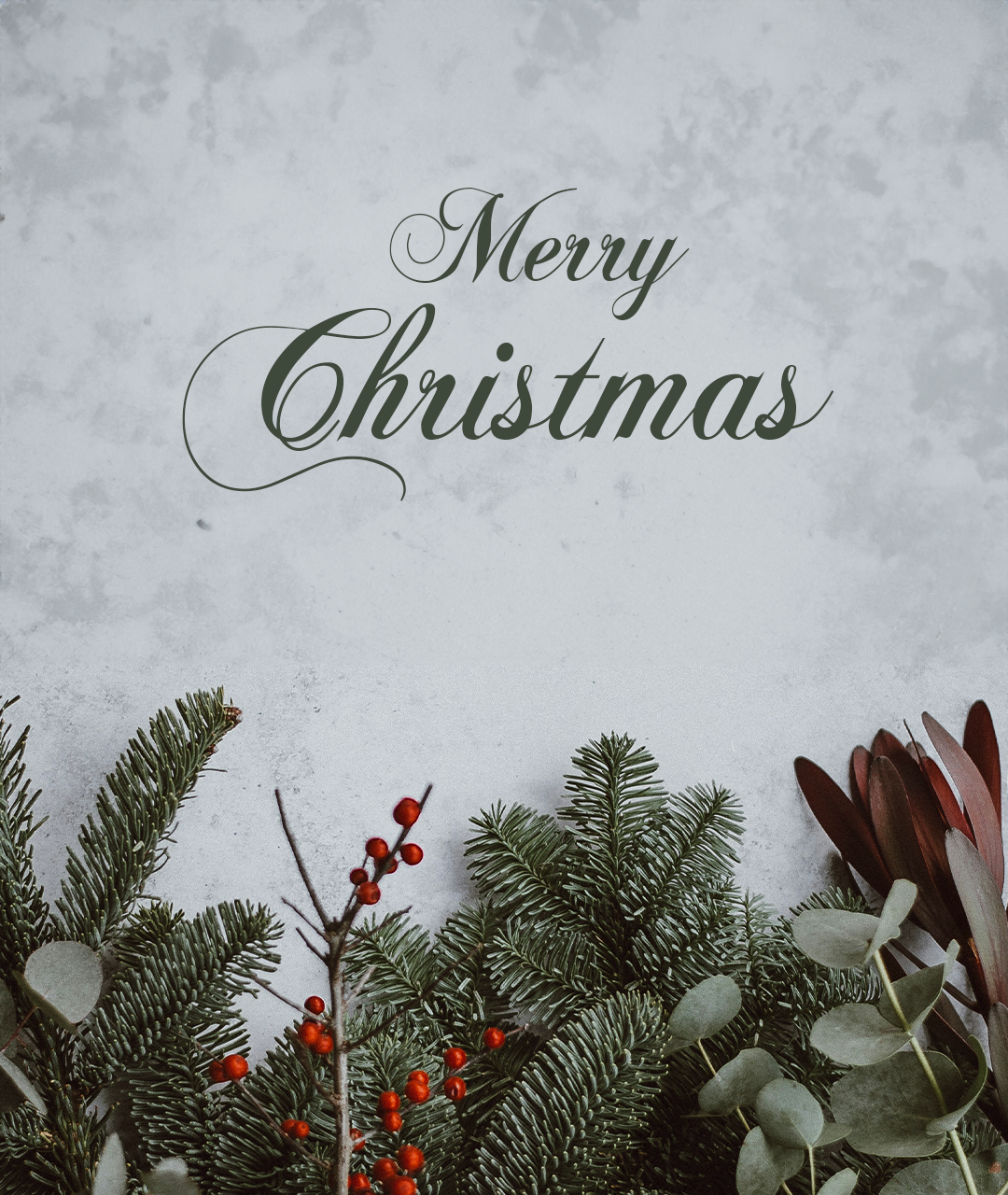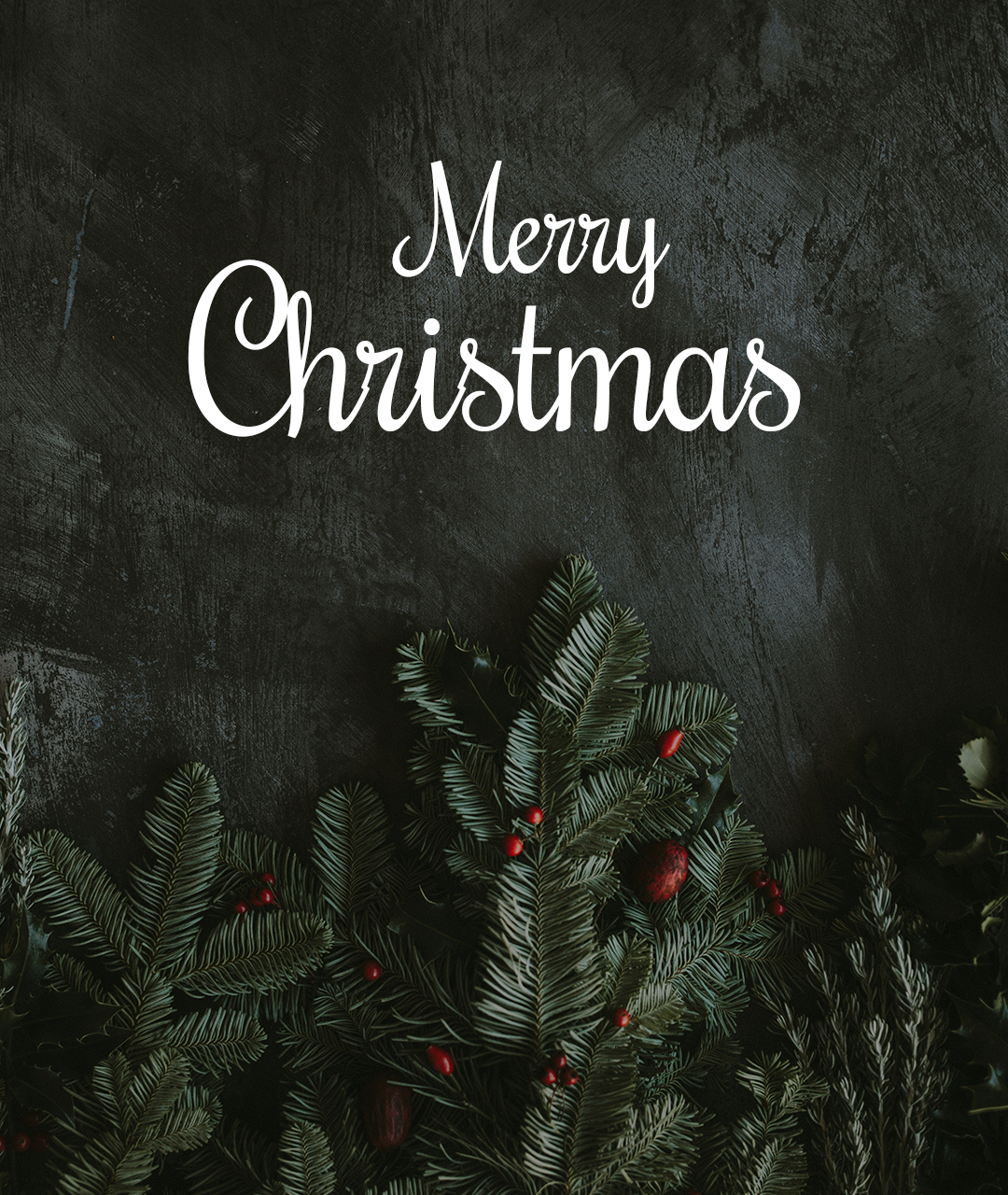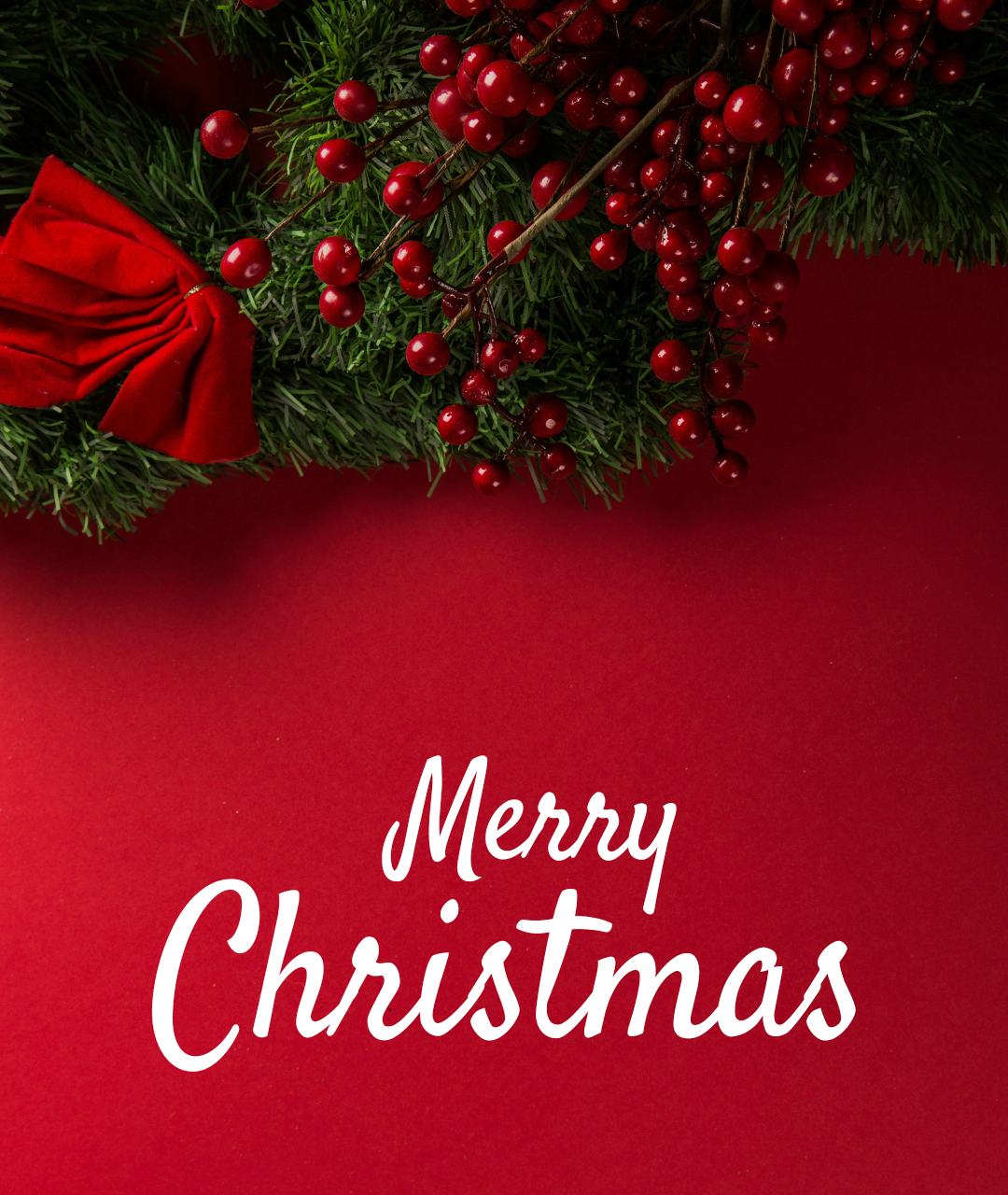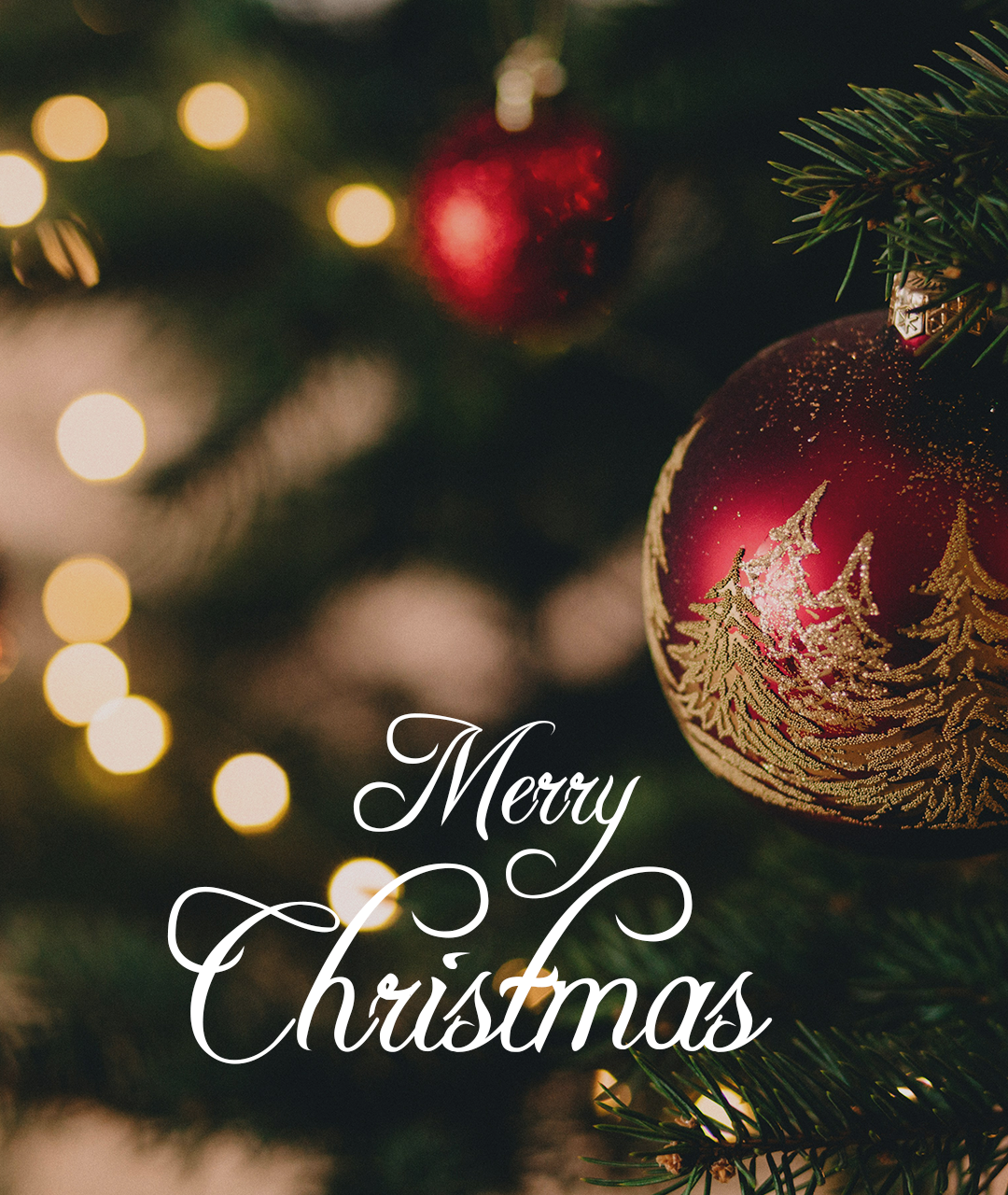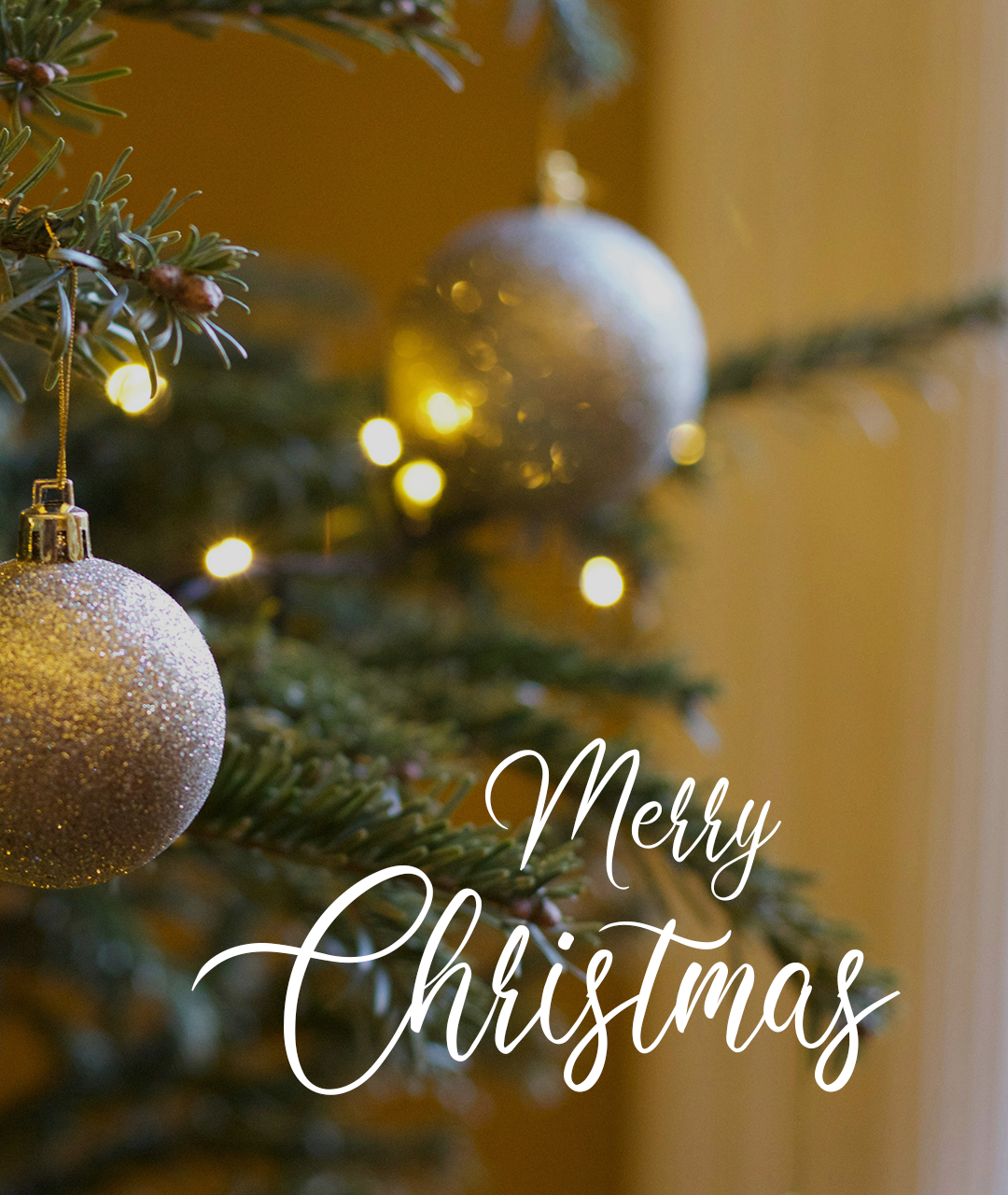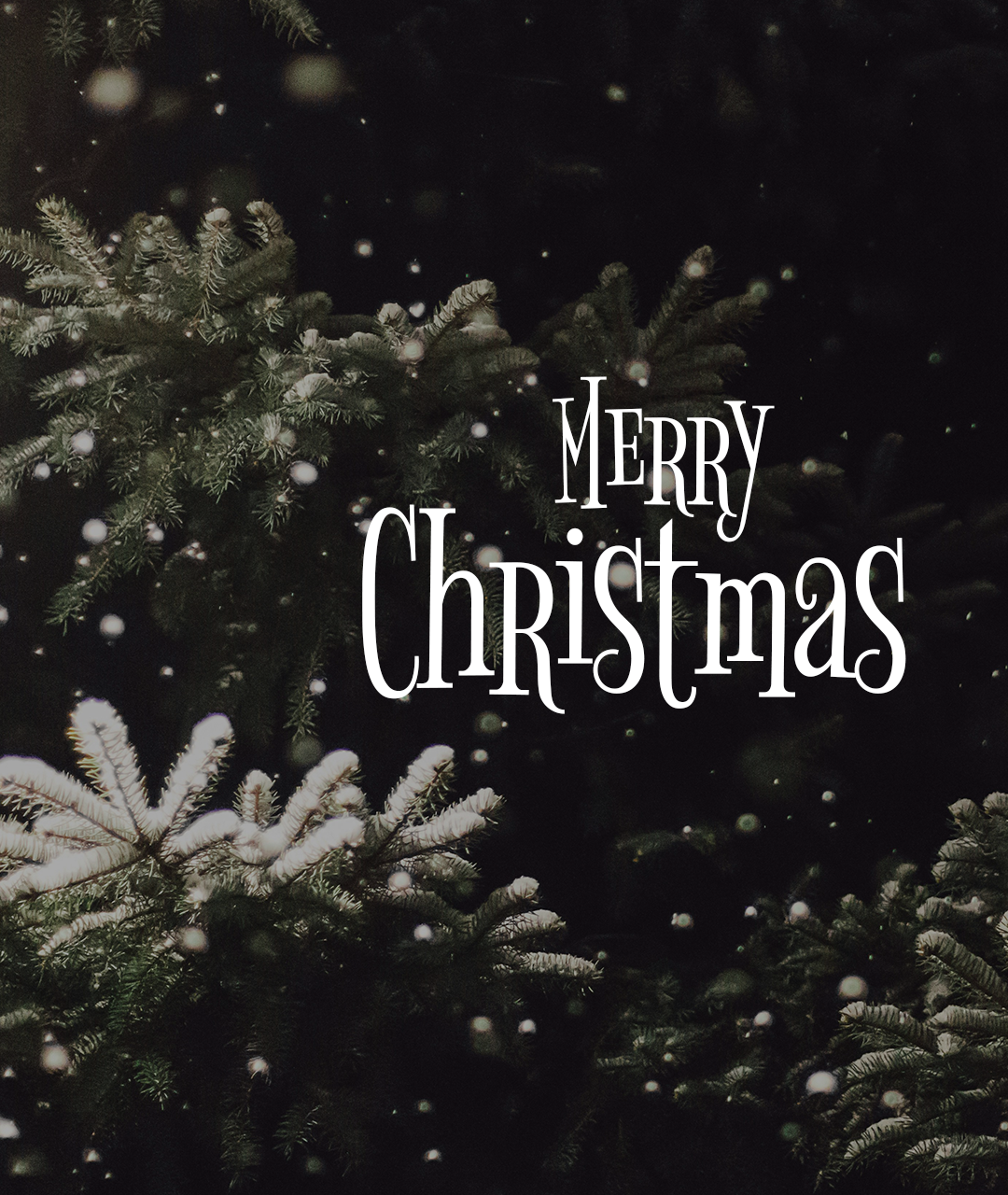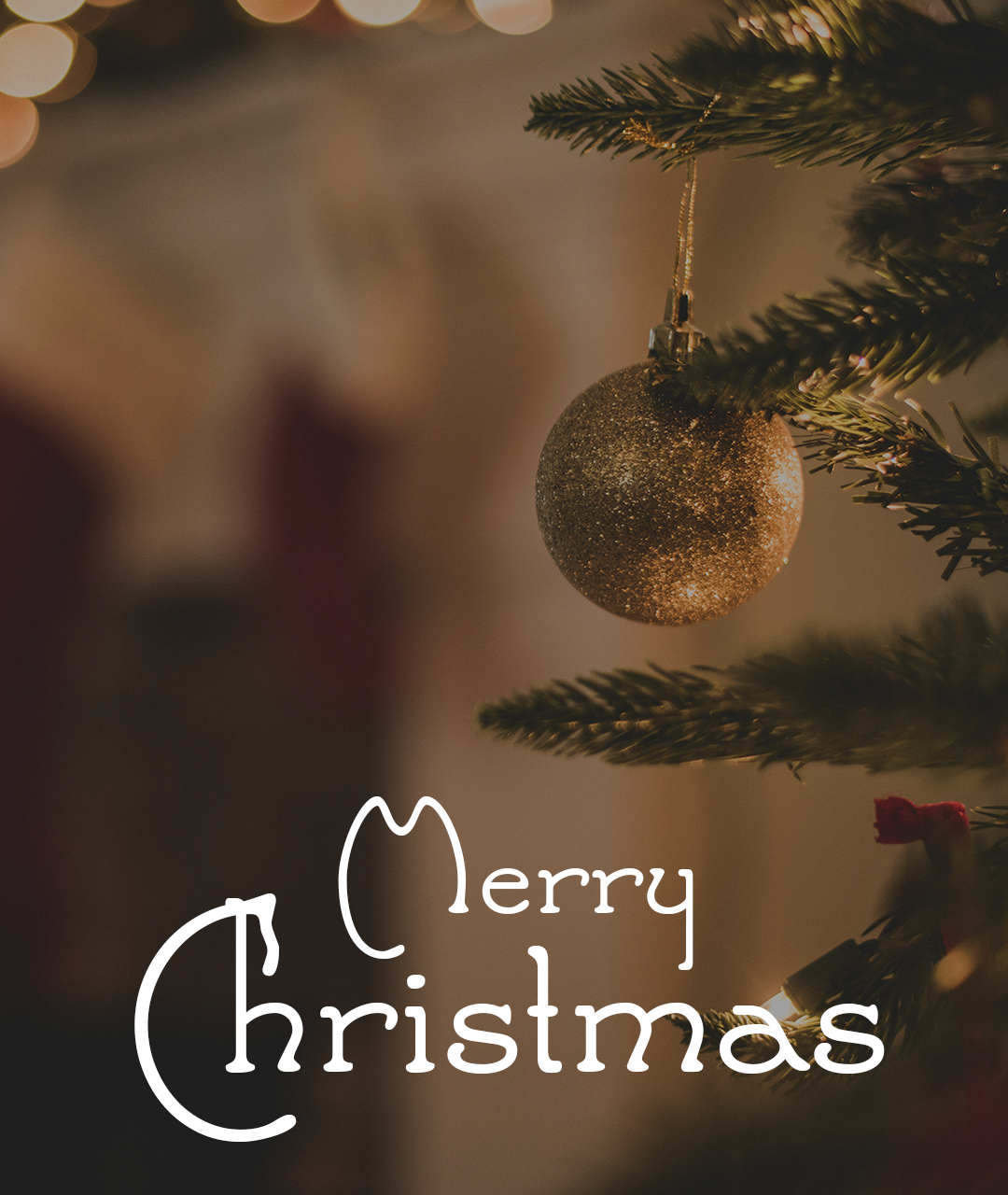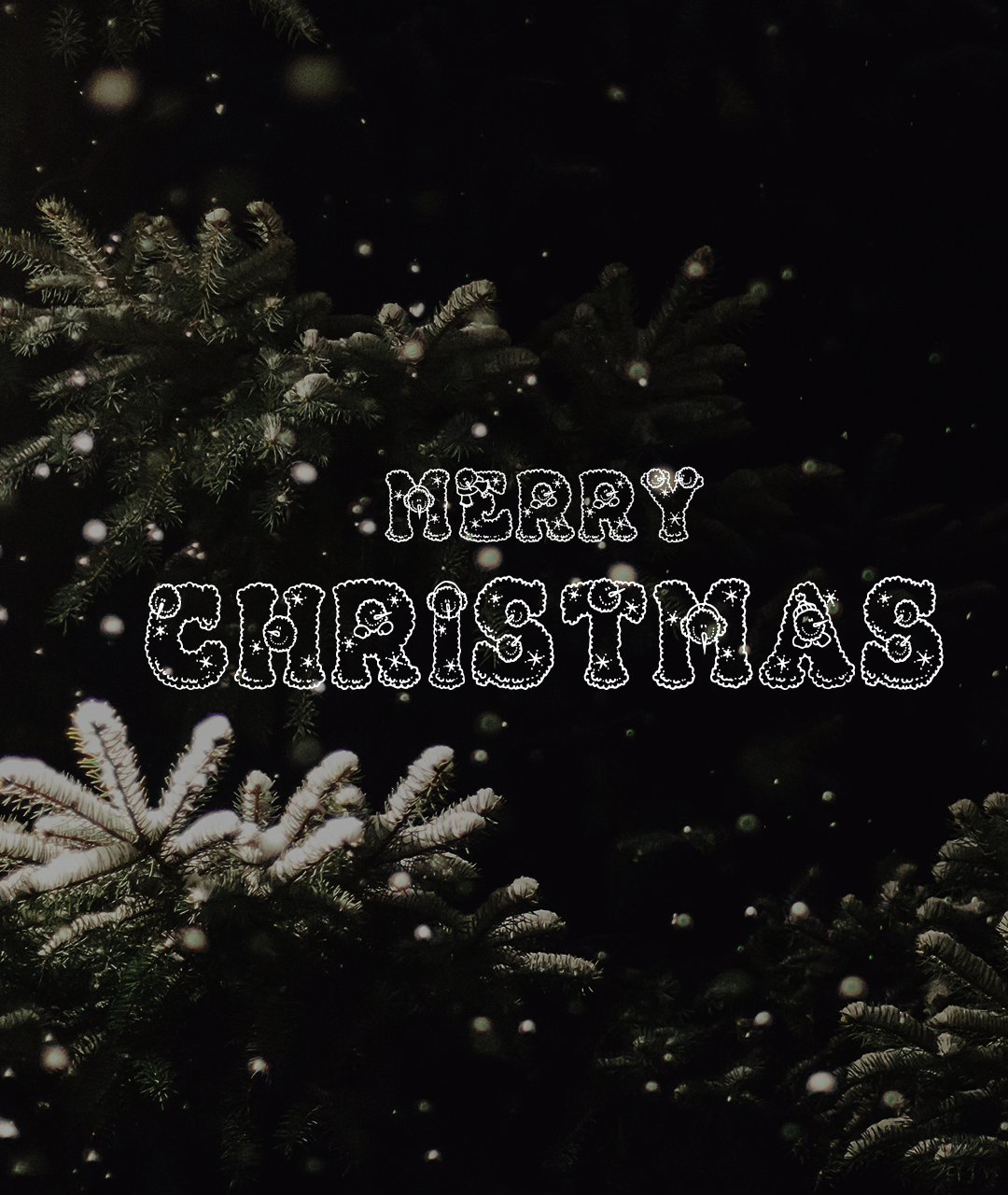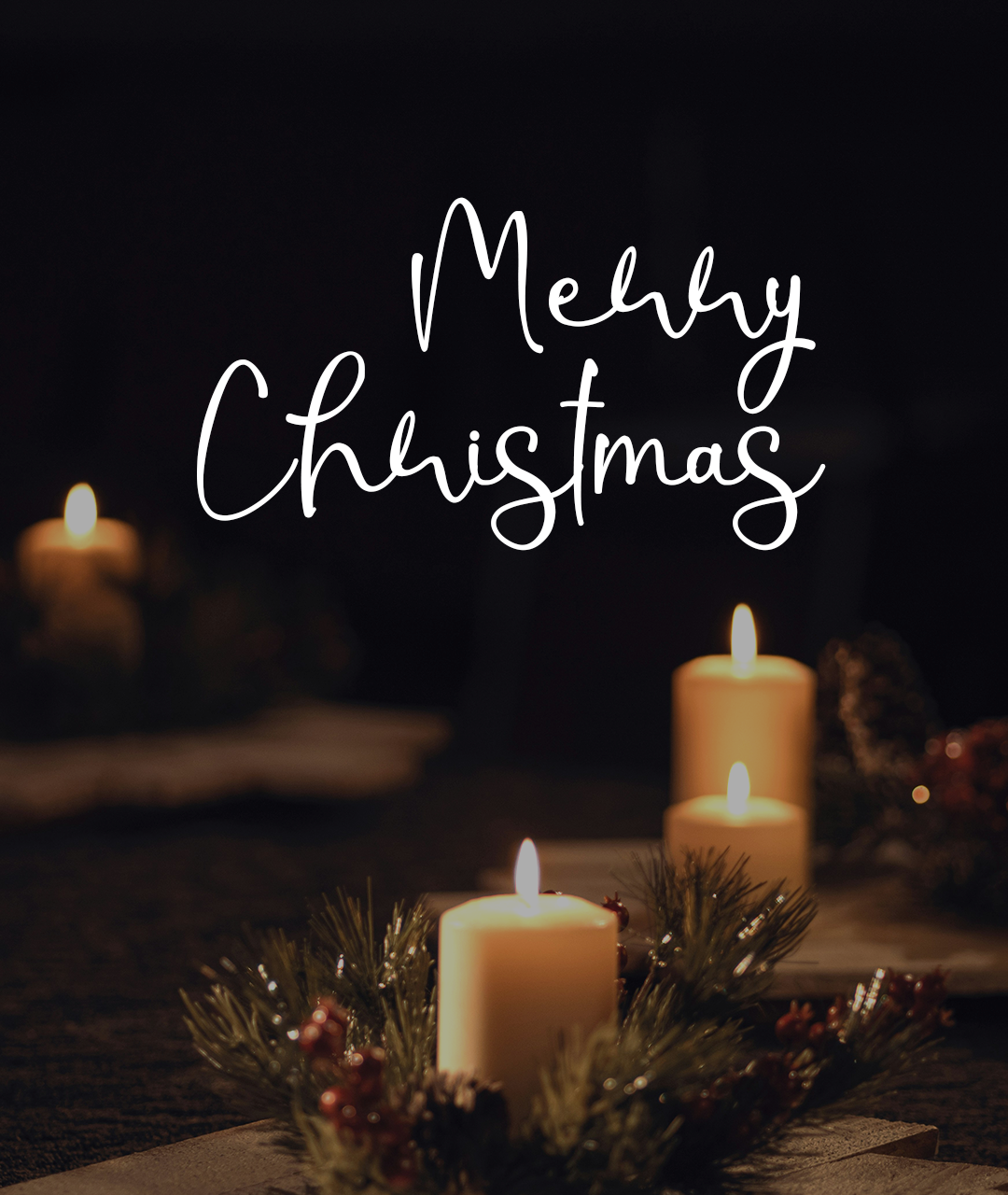
크리스마스 카드 디자인을 위한, 저작권 걱정 없는 무료 영문 필기체 폰트 9가지를 소개해 드립니다.
크리스마스나 연말 연시 새해가 되면 인사 카드를 많이 만들게 되는데요. 특히나, 크리스마스 카드는 Merry Christmas라는 영문 폰트가 차지하는 디자인 비중이 커서 다른 때보다도 폰트 선택이 디자인의 퀄리티를 좌우할 만큼 중요합니다.
1. Chopin Script font(쇼팽 스크립트 폰트)
개인은 물론 상업용도 무료로 사용할 수 있는 쇼팽 스크립트 폰트입니다. Merry Christmas라는 글씨가 크리스마스 카드에 포인트가 될 수 있을 만큼 우아한 느낌을 주는 폰트입니다.
2. Rochester (로체스터 폰트)
두번째, 크리스마스에 어울리는 영문 필기체 폰트는 구글 폰트에 로체스터 폰트입니다. 개인용, 상업용 모두 무료로 사용할 수 있으며 쇼팽 스크립트 폰트에 비해 굵기가 느껴지는 폰트로 겨울과 크리스마스 카드 제작에 더없이 잘 어울리는 아름다운 폰트입니다.
3. Satisfy 폰트
세번째, 크리스마스에 어울리는 폰트 추천은 구글 폰트에 있는 Satisfy 폰트입니다. Satisfy 폰트는, 크리스마스 카드 디자인뿐 아니라 배너나 다른 디자인에 사용하셔도 좋은 현대적인 감각의 폰트입니다.
4.Freebooter script (프리부터 스크립트)
크리스마스에 잘 어울리는 영문 필기체 폰트 4번째 소개해 드릴 폰트는, 프리부터 스크립트 폰트입니다.
첫번째로 소개해드린 쇼팽 스크립트 폰트처럼 우아하고 격식 있는 폰트로 크리스마스뿐 아니라 생일이나 다른 이벤트에 사용하셔도 좋을 아주 아름다운 폰트인데요. 개인용, 상업용 모두 무료로 사용할 수 있는 폰트입니다.
5. Clarissa 클라리사 폰트
디자인에서 폰트는 비슷하게 보이는 폰트도, 미세하게 느껴지는 한 끗 차이로 디자인의 퀄리티가 확연하게 차이나는 경우가 많습니다. 특히, 크리스마스나 생일 카드 같은 경우에는 영문 폰트가 디자인을 좌우하는 경우가 큽니다.
6.Bigelow Rules 폰트
Bigelow Rules 폰트는 마법같은 느낌을 주는 특별한 영문 필기체 폰트입니다. 이 폰트 또한, 개인용과 상업용 모두 제한 없이 사용할 수 있는 폰트입니다. 아래, 이미지를 클릭하시면 다운로드하실 수 있습니다.
7. Santa's Sleigh 폰트
Santa's Sleigh 폰트는 클래식한 분위기의 영문 필기체 무료 폰트로 크리스마스뿐 아니라 다양하게 사용할 수 있는 폰트입니다. 특별한 느낌의 폰트를 찾고 계시는 분들이라면 아마도 "와~~" 감탄사가 나올지도 모릅니다.
처음 이 폰트를 찾고, 저 역시 그랬거든요. 이 폰트 역시 개인은 물론 상업용까지 무료로 사용하실 수 있는 폰트입니다.
8. Snowpersons 폰트
Snowpersons 폰트는 마치, 눈사람이 연상되는 귀엽고 재미있는 느낌의 겨울 크리스마스 테파 폰트입니다. 복잡한 배경보다는, 단순하고 귀여운 배경에 잘 어울리는 폰트입니다. 이 폰트도 개인 및 상업용 사용이 모두 가능한 폰트입니다. 아래 이미지를 클릭하시면 다운로드하실 수 있습니다.
9. Christmas Shine 폰트
Christmas Shine 폰트는, 개인적으로 제가 이번 크리스마스 카드 제작에 사용하기 위해서 찾은 폰트입니다. 서체만으로 크리스마스 분위기를 연출할 수 있는 필기체 폰트입니다.